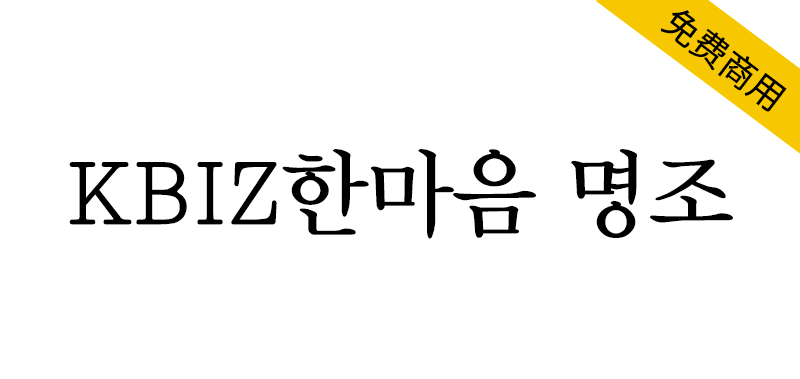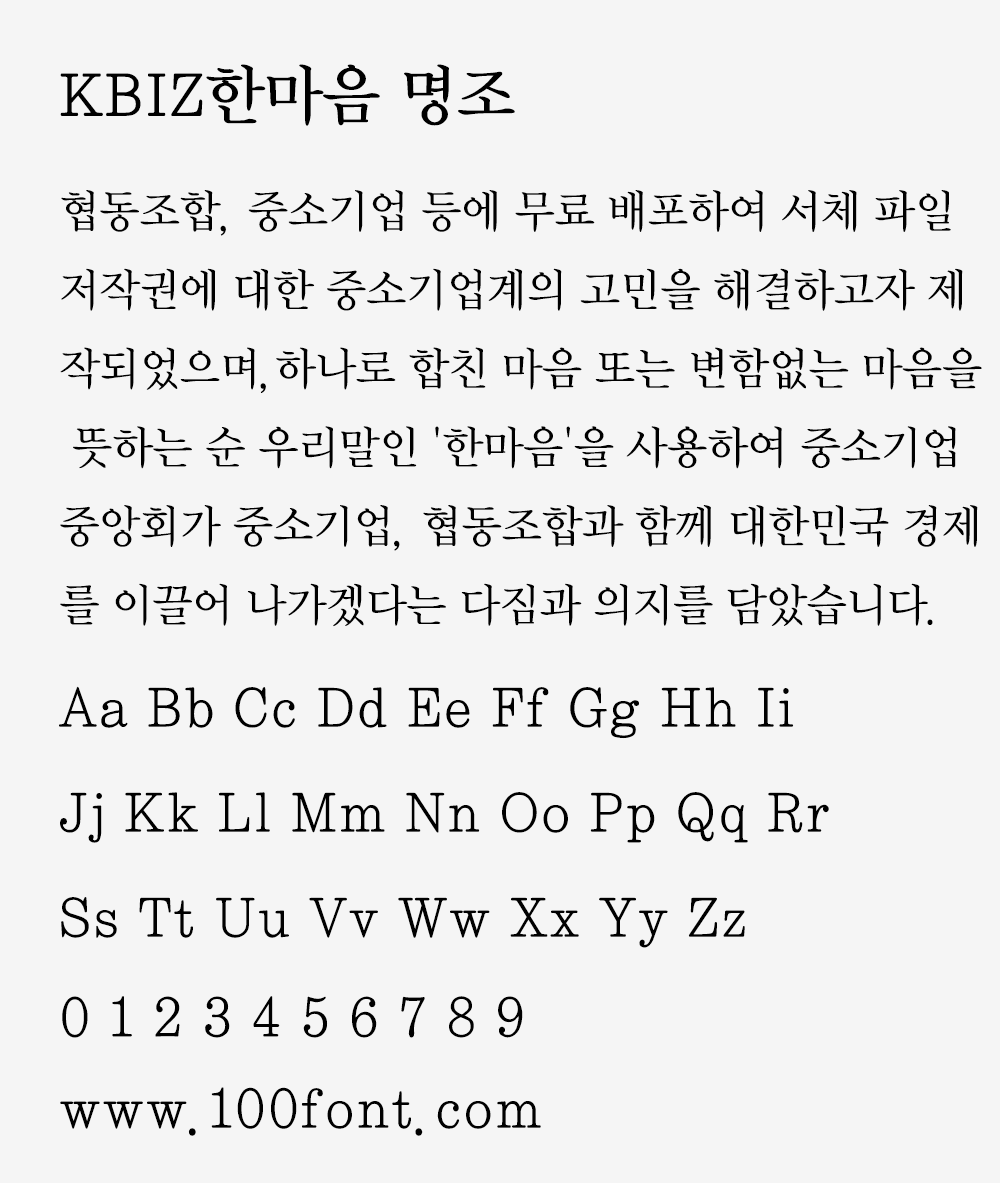
KBIZ한마음 명조免费分发给合作社、中小企业等,旨在解决中小企业界对字体版权的苦恼。使用意为团结一致的心或不变的心的纯韩语 “ 한마음 ” ,表达了与中小企业和合作社一起引领大韩民国经济的决心和意志。
협동조합, 중소기업 등에 무료 배포하여 서체 파일 저작권에 대한 중소기업계의 고민을 해결하고자 제작되었으며,하나로 합친 마음 또는 변함없는 마음을 뜻하는 순 우리말인 '한마음'을 사용하여 중소기업중앙회가 중소기업, 협동조합과 함께 대한민국 경제를 이끌어 나가겠다는 다짐과 의지를 담았습니다.